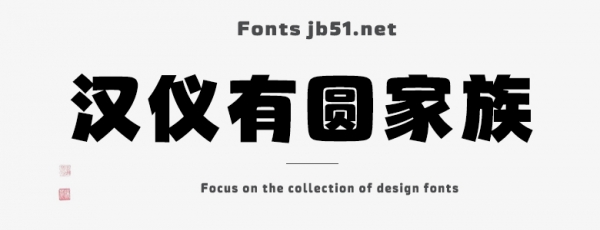
漢儀有圓家族是由漢儀字庫出品,字體由細到粗,總共包含7個字重,實現(xiàn)從細體到粗體的平滑過渡。細體強調(diào)線條質(zhì)感、明快透亮,筆畫富有韌性,適合應(yīng)用于藝術(shù)設(shè)計、平面宣傳設(shè)計、網(wǎng)頁設(shè)計,書法字帖等領(lǐng)域,需要的朋友可以前來本站下載。
漢儀有圓家族是由漢儀字庫簽約設(shè)計師曹文強老師設(shè)計的一套“寓圓于黑”的字體家族。這款字體從篆書碑刻的線條中汲取靈感,將黑體的理性和圓體的溫柔結(jié)合在一起,讓您的文字看起來溫文爾雅,擺脫尷尬。而家族化的設(shè)計,也意味著這套字體可以勝任不同類別、多種層次的復(fù)雜排版環(huán)境,讓您的版式效果更為統(tǒng)一。
漢儀有國家族采用參數(shù)化設(shè)計,由細到粗,總共包含7個字重,實現(xiàn)從細體到粗體的平滑過渡。細體強調(diào)線條質(zhì)感、明快透亮,筆畫富有韌性;粗體強調(diào)字形的塊面感,珠圓玉潤、溫和細膩。字重豐富的家族化設(shè)計,有利于復(fù)雜版式的處理,可以將字體應(yīng)用在不同視覺層級的不同位置,統(tǒng)一版式的視覺風(fēng)貌,豐富版面效果。